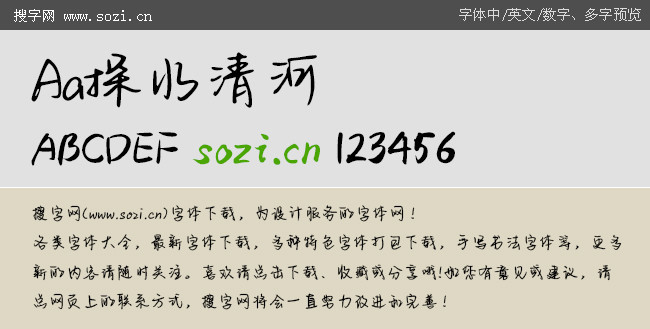
Aa探水清河
搜字網(wǎng)給大家提供一款A(yù)a探水清河中文字體下載,這是一款手寫(xiě)風(fēng)格的書(shū)法字體,字體書(shū)寫(xiě)流暢,字形瀟灑大方,適合海報(bào)設(shè)計(jì)、畫(huà)冊(cè)等宣傳廣告等應(yīng)用(此字體為個(gè)人非商用版,如需商用請(qǐng)聯(lián)系作者購(gòu)買版權(quán))。